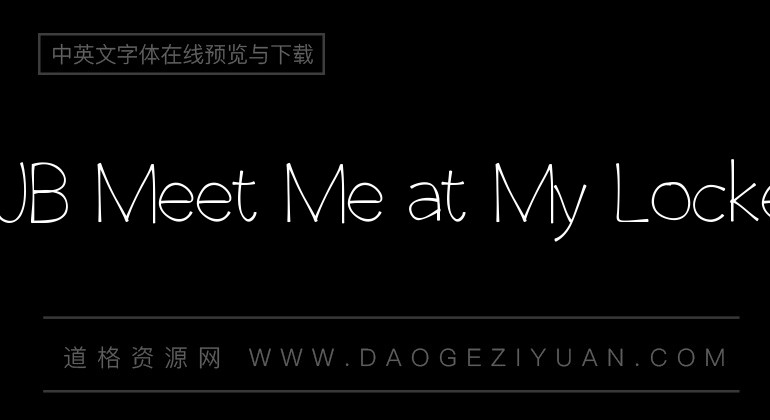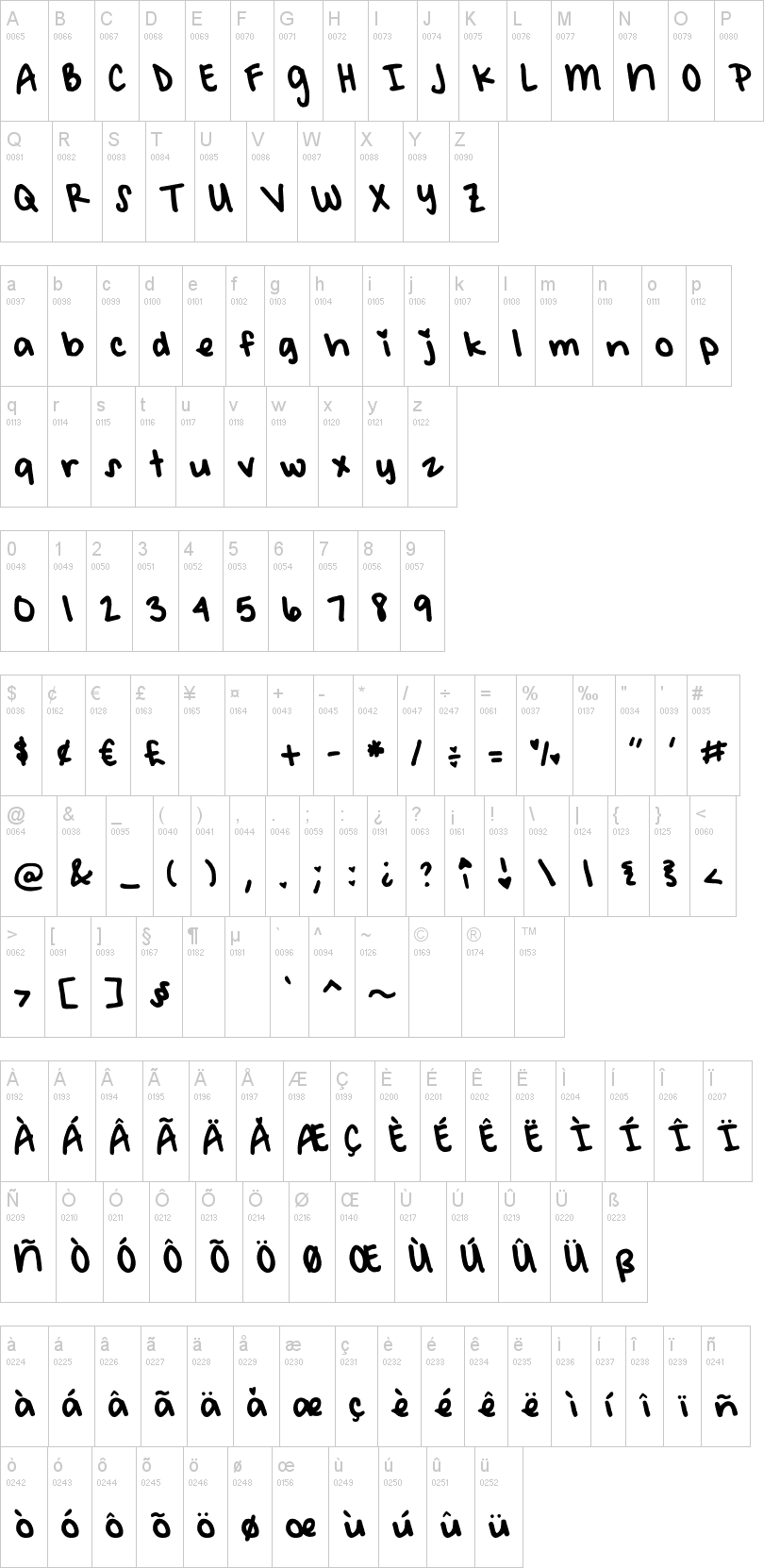
DJB Meet Me at My Locker 字体是由DeeJay Bauerschmidt设计的一款手写字体。它是一款细腻而精致的手写字体,具有流畅的线条和温暖的色调,充满自然的气息。它的字形具有细腻的质感,可以给文字带来柔和的气氛,提供舒适的视觉效果。它的字体特点是字母的起伏自然,给人以温暖的感觉。它的字形简约而优雅,适合用于各种印刷品和网页设计,也可以用于各种宣传活动和商业活动的标识和宣传材料中。内容介绍
DJB Meet Me at My Locker是一款非常不错的手写艺术字体,具有很好的视觉感,适合于文化类的宣传设计、商业类品牌的广告和产品包装设计以及个性化文字排版等较多场景。